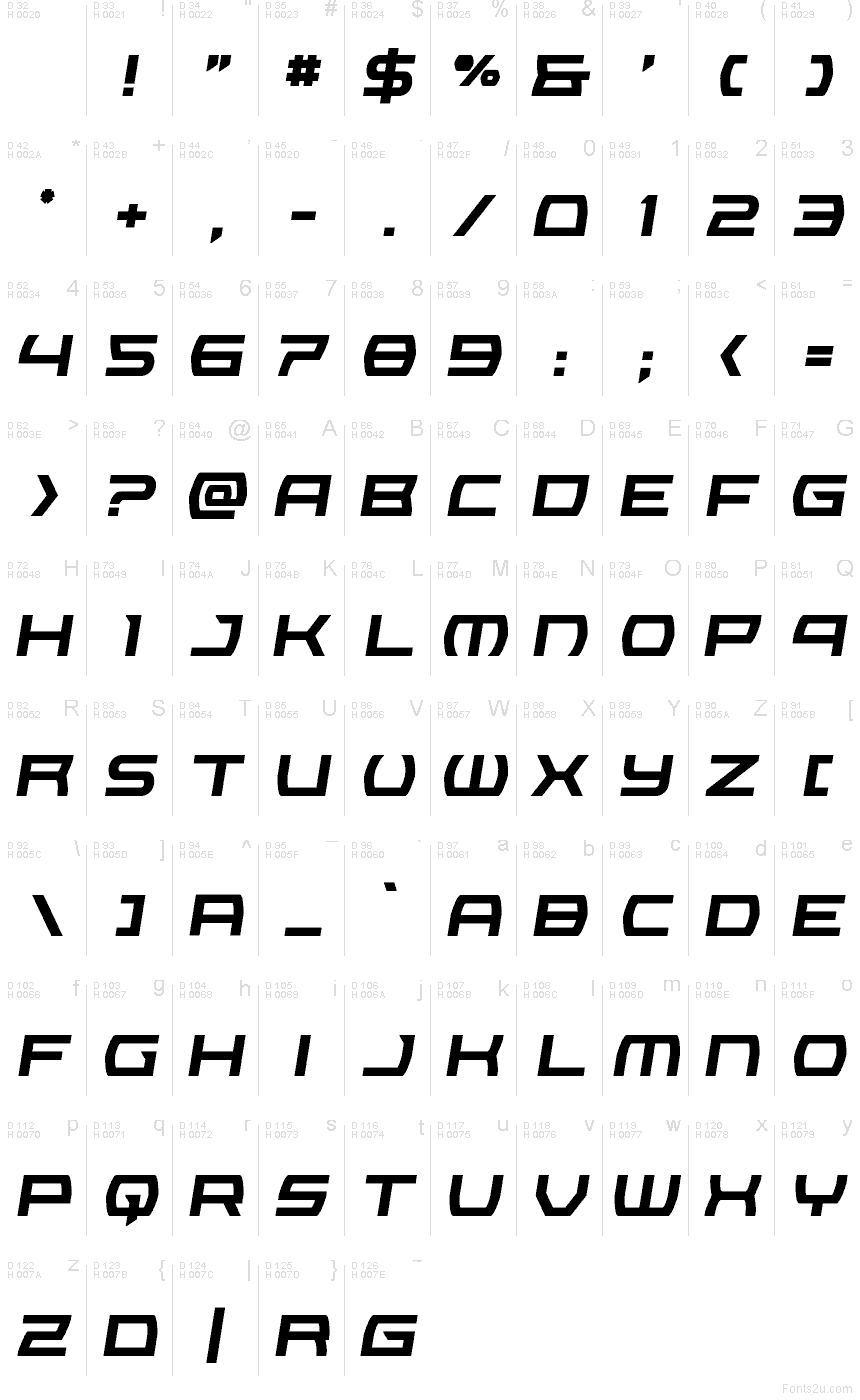
Icemaster Bold Semi-Italic
Icemaster Bold Semi-Italic von Iconian Fonts ist eine kostenlose, futuristische Display-Schrift mit einem rasanten, eisigen Neigungswinkel. Die Buchstaben wirken wie aus dicken schwarzen Streifen gemeißelt und zeichnen sich durch abgerundete Ecken, eng anliegende horizontale Verbindungen und weite Öffnungen aus – das verleiht dem gesamten Design einen schlanken, maschinellen Rhythmus.
Sie eignet sich hervorragend für Sci-Fi-Plakate, Gaming-Logos, Tech-Branding, Streaming-Thumbnails und Titelkarten, bei denen es auf Schnelligkeit statt auf Sanftheit ankommt. Als kostenlose Schrift passt sie zudem perfekt zu Cover-Texten und kompakten Wortmarken, da die dynamische Vorwärtsneigung und die kräftigen Formen selbst kurzen Phrasen eine energiegeladene, zielgerichtete Wirkung verleihen.